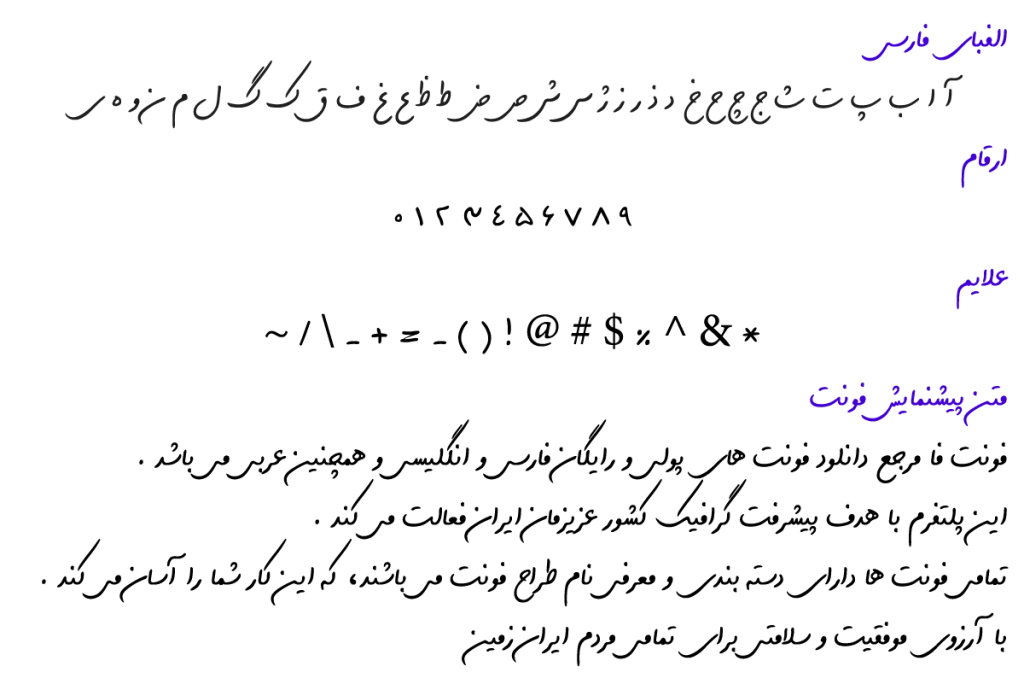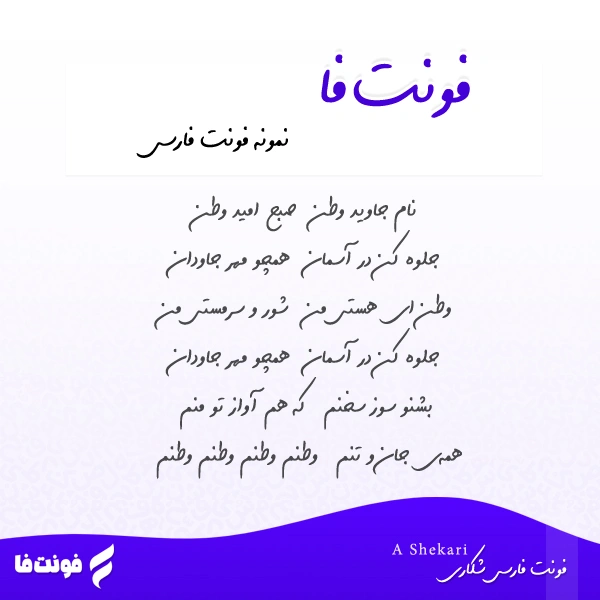
فونت فارسی شکاری – A Shekari
نوع فونت: فونت دست نویس
توضیحات و معرفی فونت شکاری
فونت فارسی شکاری ( A Shekari ) از مجموعه فونت های آزاد می باشد، و نیز نوع فونت دست نویس می باشد.
فونت خوشگل مربوط توسط امید مرادی در سال 1390 طراحی و ساخته شده است.
و نیز فونت A Shekari در یک وزن معمولی است.
- A Shekari Regular
پیش نمایش این تایپ فیس را که شعر زیبای «وطن» با آن نوشته شده، در تصویر زیر مشاهده میکنید.